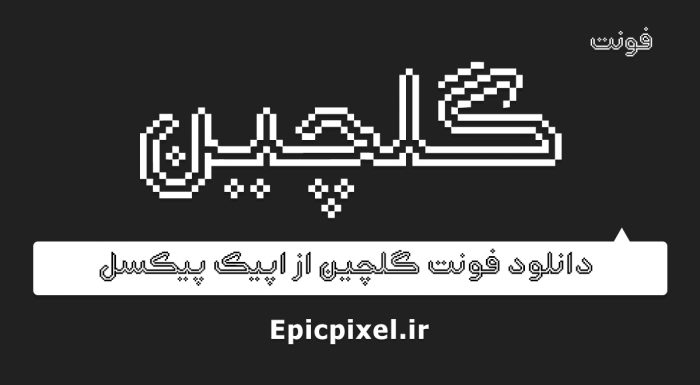
| ⭐ توضیحات | مجموعه ای کامل از فونت های گلچین و نسخه شبیه سازی شده اپیک گلچین فونت اپیک گلچین با پشتیبانی از حروف فارسی ، اعداد فارسی Fu Num (بدون حروف انگلیسی ) |
فونت گلچین یک فونت پیکسلی باستانی فارسی
فونت گلچین از خط کوفی بنایی خوشنویسی گرفته شده و جزء فونت های تزئینی است (ساقه گنبدی)
این حروف که معمولا روی ساقه گنبد ها و گاهی روی سردرها و حتی کتیبهٔ ایوان ها طراحی و اجرا می شوند، بر پایه خطوط مانند کوفی،ثلث، و برخی دیگر از اقلام خوشنویسی هستند که روی شبکهٔ شطرنجی نقش می بندند و قانون ترسیم آن ها با سایر مثال ها کمی فرق دارد. ماهر النقش آن را با نام ساقه گنبدی معرفی می کند.